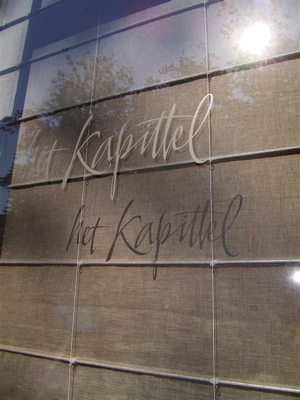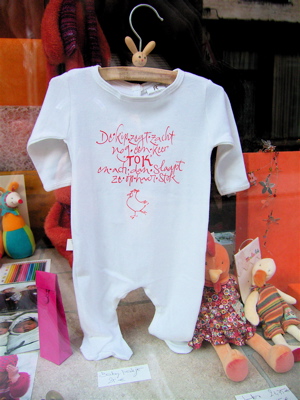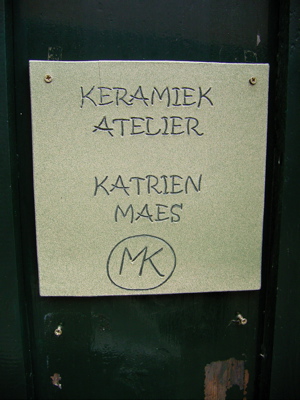
ヨーロッパでカリグラフィーロゴ
8月最後の日には、ヨーロッパで見つけた素敵な手書き文字をご紹介します。
とれも美しく素敵ですよ。
やはり手書きはいいよね〜。
どなたのデザインなのかわかりませんが、やはり手書きから作られる文字は素敵。本当に美しい。
石に彫ったこのただの25Aですが、いいですね〜。この5の形、味があります。
やはりレストランやお菓子屋さんが、こういうイタリック体の流れるラインの文字の看板が多いですね。すべて入ってみたかったです。
う〜ん!可愛い・・・!
文字とニワトリがぴったり合ってます。
もっともっと探せば見つかったことでしょう。手書きの美しいカリグラフィー文字を見つけた時の嬉しさ。